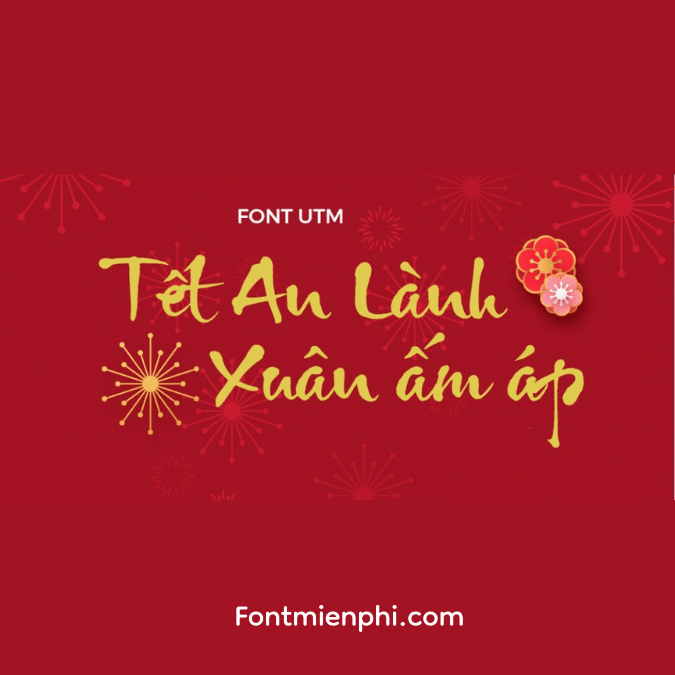
Việt hóa font UTM Ông Đồ Già ,font tết
Việt hóa font UTM Ông Đồ Già
Font UTM Ông Đồ Già là một loại font chữ được thiết kế đặc biệt để mang đậm nét văn hóa Việt Nam, phù hợp cho các dịp lễ Tết. Font này thường được sử dụng trong các sản phẩm truyền thông, thiệp chúc Tết, và trang trí không gian ngày Tết.
Đặc điểm nổi bật:
• Phong cách chữ: Được thiết kế với những đường nét mềm mại, tinh tế, phản ánh sự duyên dáng của văn hóa Việt Nam.
• Tính ứng dụng: Phù hợp cho việc tạo ra các sản phẩm như thiệp Tết, banner trang trí, và các ấn phẩm văn hóa khác.
• Tình cảm và ý nghĩa: Gợi nhớ về truyền thống và phong tục tập quán trong dịp Tết Nguyên Đán, giúp mang lại không khí ấm cúng và sum vầy.
Font UTM Ông Đồ Già không chỉ là một công cụ hỗ trợ trong việc thể hiện văn bản mà còn là cầu nối giữa quá khứ và hiện tại trong văn hóa Việt Nam.